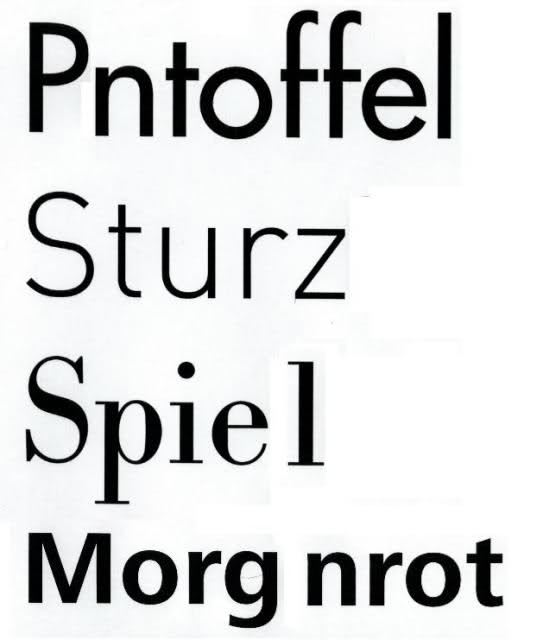
Um welche Schriften handelt es sich ?
Es geht um die obigen Schriften. Im Verdacht hatte ich Bodoni, Rotis, Univers und new courier, allerdings sehen die dann an manchen Stellen etwas anderst aus.
Futura Medium
DIN-Light Alternate
Bodoni Nr1 SH-Regular
Frutiger 65 Bold
DIN-Light Alternate
wie kannst du denn anhand der in ›sturz‹ verwendeten buchstaben zwischen einer normalen ›din light‹ und einer ›din light alternate‹ unterscheiden? meines wissens sind die formen dieser buchstaben in den beiden varianten identisch, und im empfehlenswerten opentype-format gibt es diese differenzierung ohnehin nicht mehr.
wie kannst du denn anhand der in ›sturz‹ verwendeten buchstaben zwischen einer normalen ›din light‹ und einer ›din light alternate‹ unterscheiden? …
gar nicht, lieber Thierry :? Ich hab nur wtf nachgeplappert :D